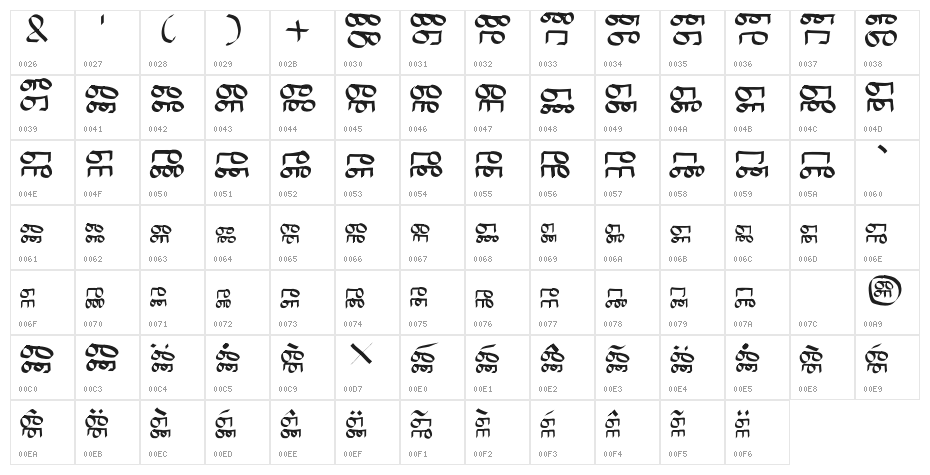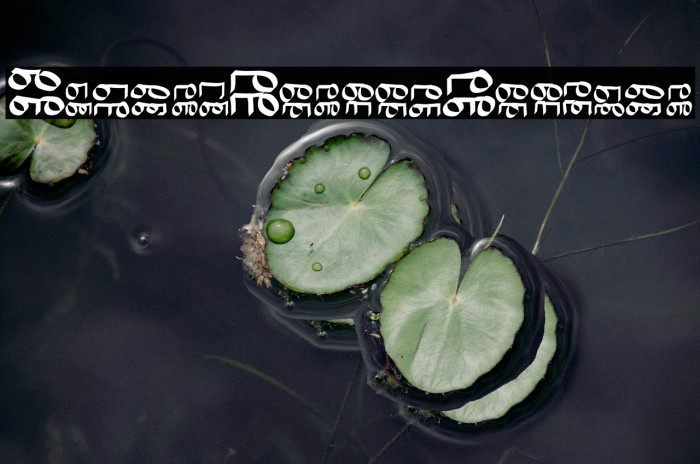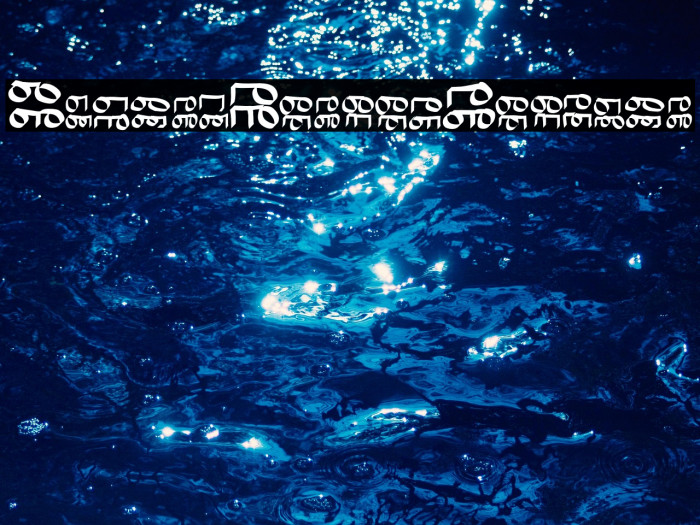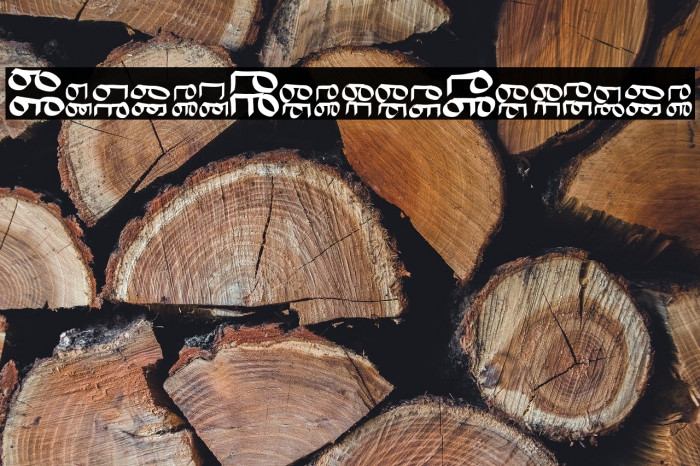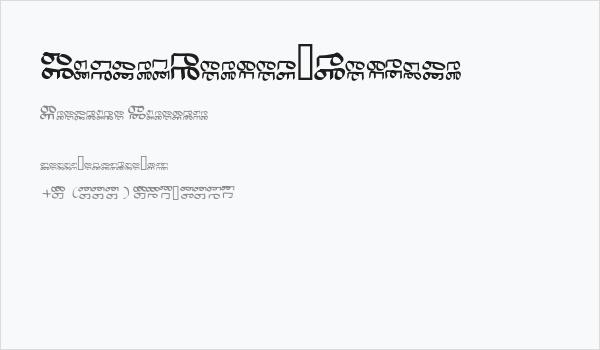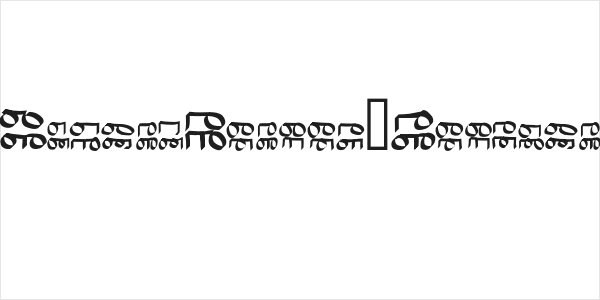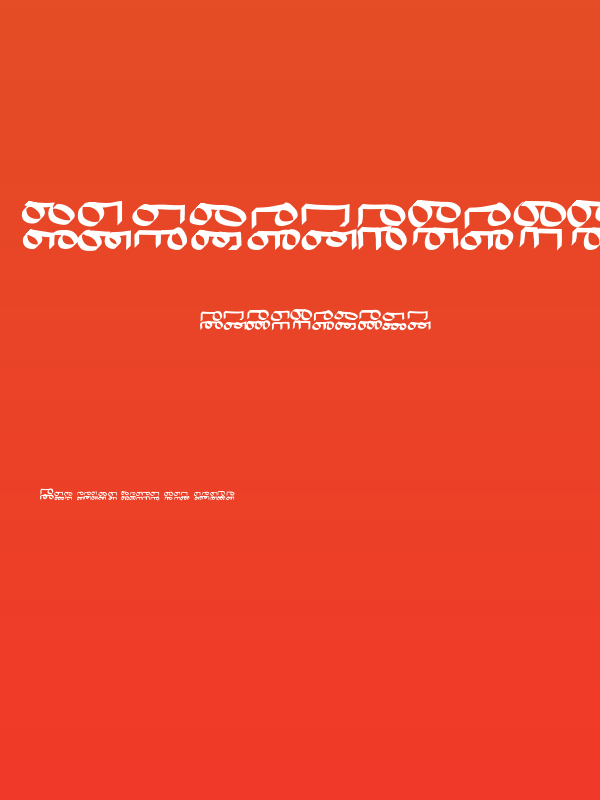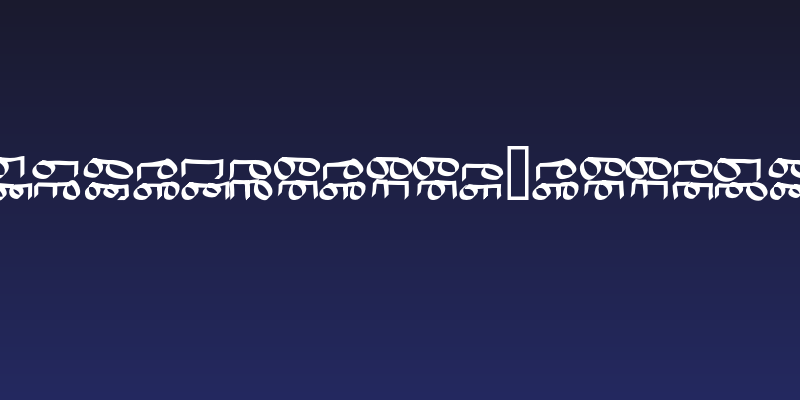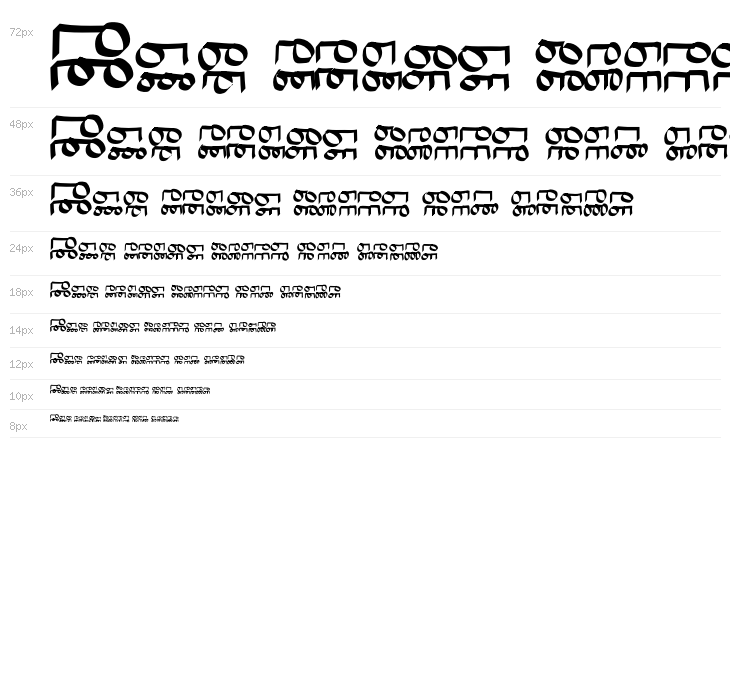
BinaryVerges-Regular Font
| Stil general | Futuristic, Abstract |
| Caz de utilizare | Logos, Posters, Artistic Designs |
| Proiecte propuse | Ideal for sci-fi themed designs, artistic posters, or branding that requires a unique and futuristic look. |